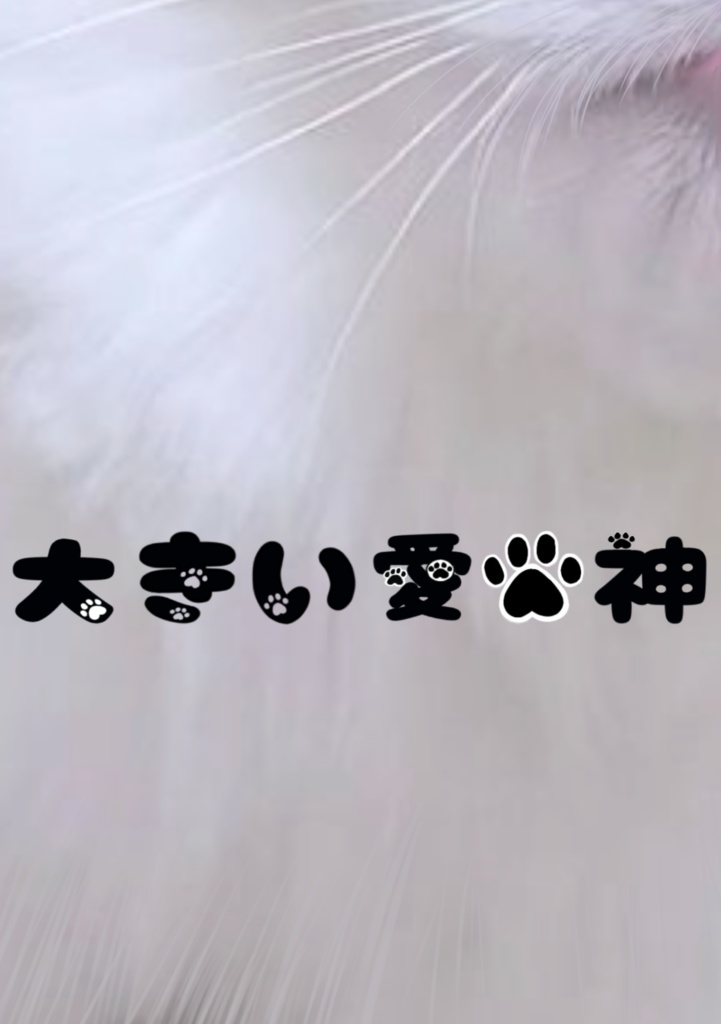
犬猫のにくきゅうフォント
手書きのカワイイ肉球を散りばめたフォント集です。 ******************************************************************** 有料フォントご購入の際はこちらのお約束をお読みください。 購入した時点でお約束を理解・同意したものとします。 ・個人・商用共に違法性が無いものであればご自由にお使いいただけます。(LINEスタンプ・きせかえでのご利用もOKです) ・LINEクリエイターズ絵文字での利用は禁止とさせていただきます。(LINEスタンプ・きせかえでのご利用→OK、LINE絵文字でのご利用→NG) ・複数人でご利用になる際は、それぞれ購入をお願いいたします。 ・フォントファイル自体の改変・改造(ttfやotfファイル自体の中身に手を加えること:フォントを打ち出したものの加工などはOKです)・再配布・販売・webへのアップロード(webフォントとしての利用含む)は禁止いたします。 ・フォントを使ったロゴ等の商標登録はご遠慮ください。 ・フォントを使用したことによるいかなる損害、トラブル、ウィルス感染などに関して、制作者「ことぶき」は責任を負いません。自己責任でのご利用をお願いいたします。 ・技術的なサポートはしておりません。自己責任でご購入・ご利用ください。 ・予告なくフォントの販売を終了する場合がございます。 ・購入された方はフォントの使用権を購入したものであり、フォントの権利や著作権は「ことぶき」に帰属します。